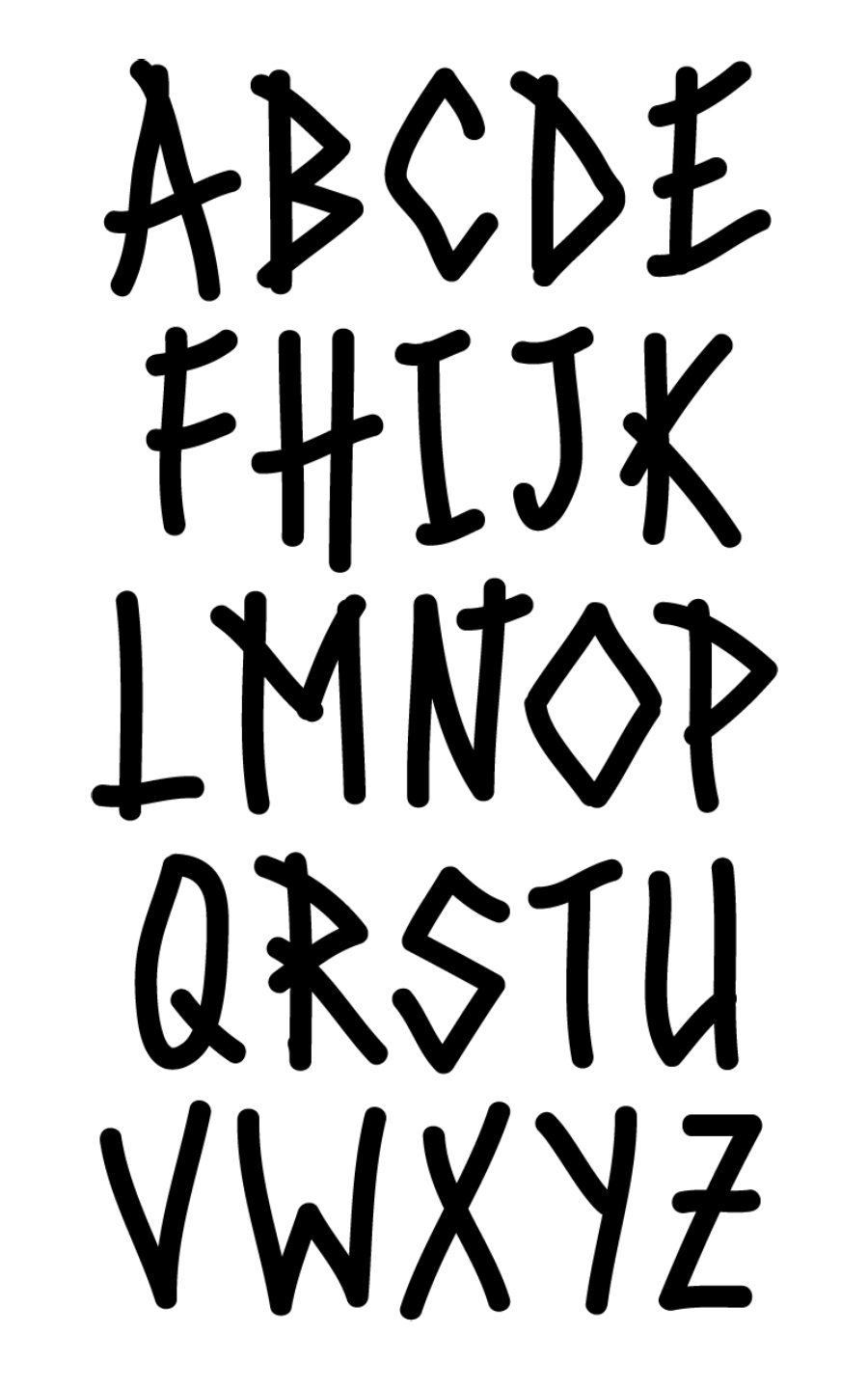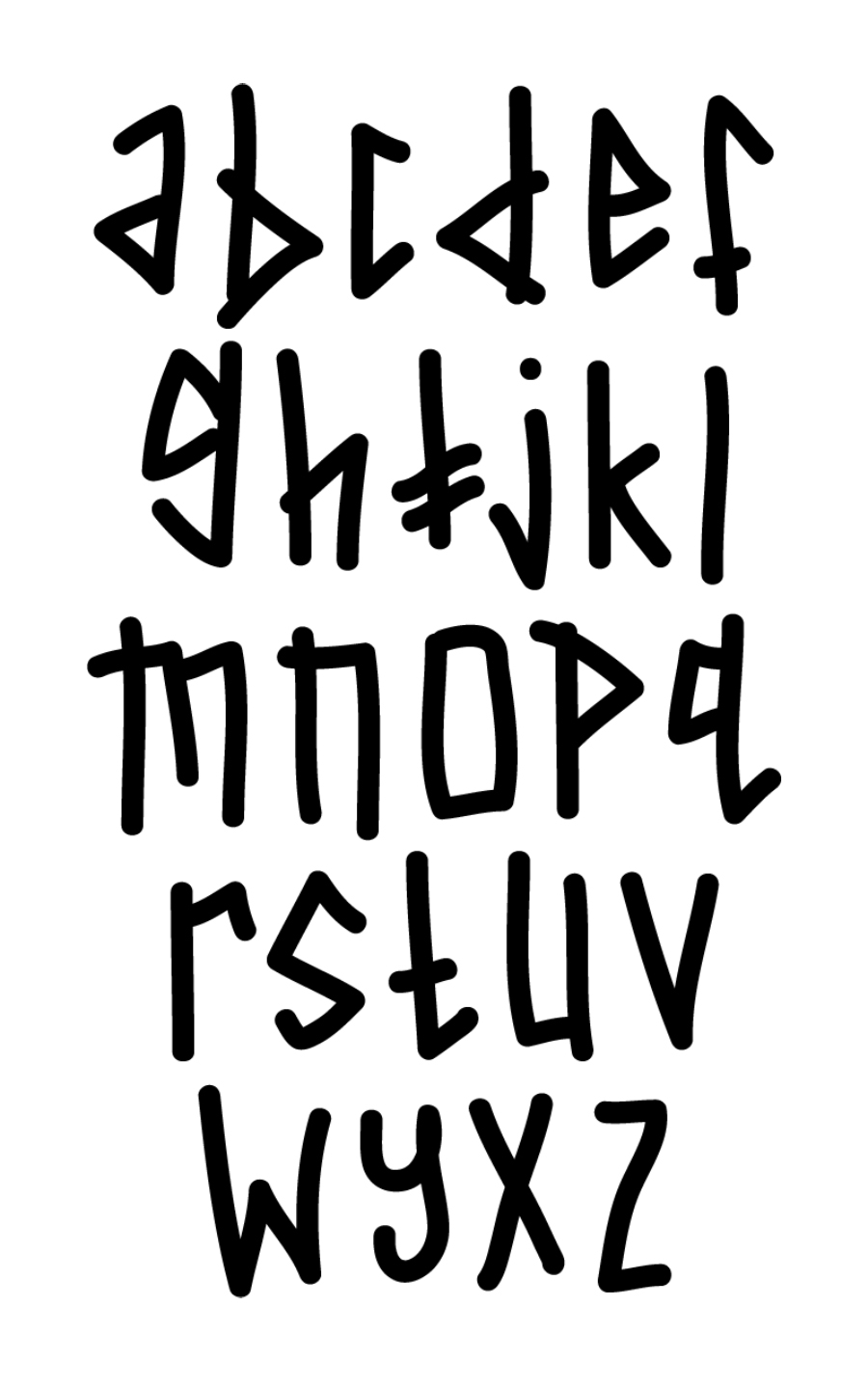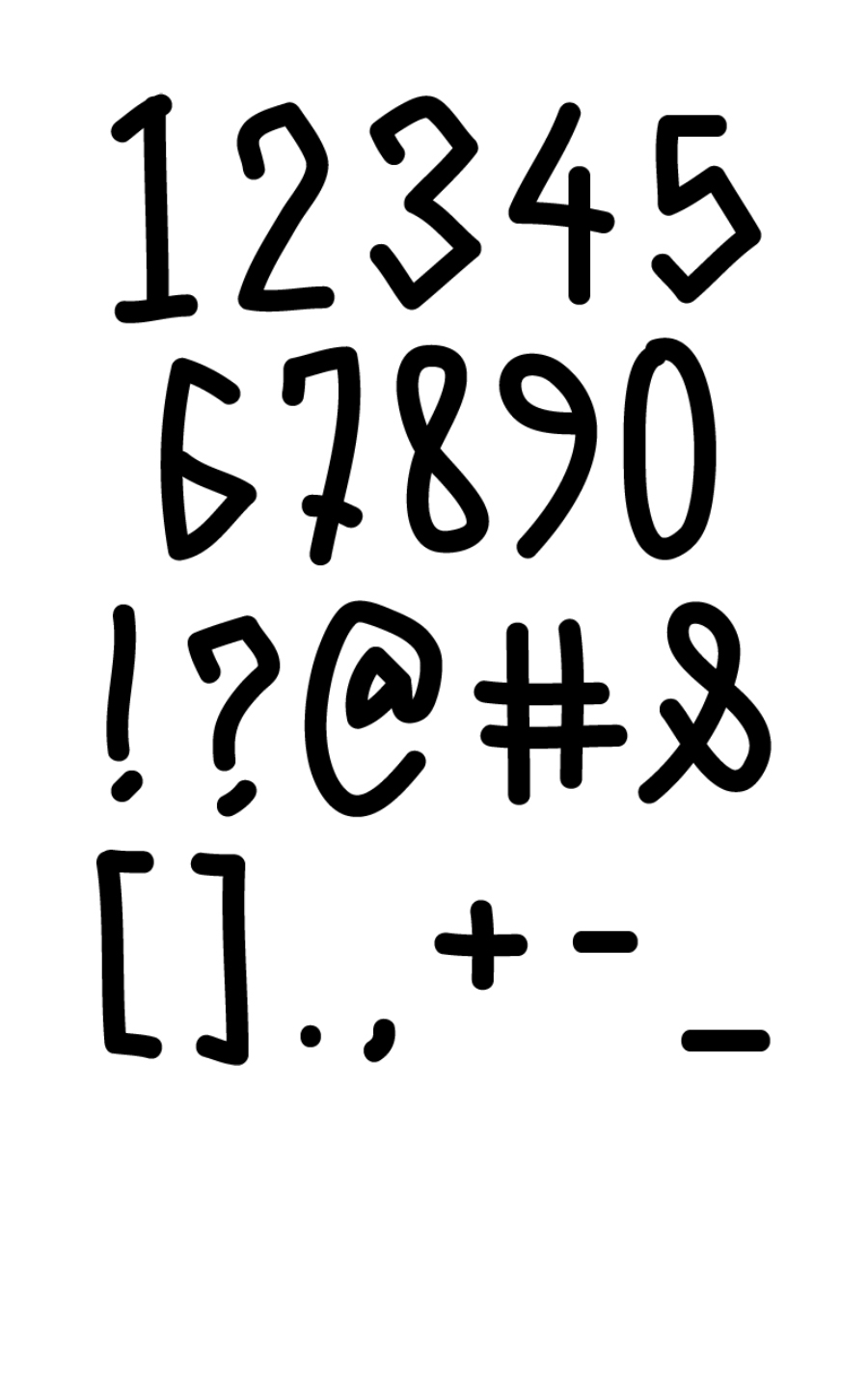
威基基日落免费字体
Waikiki Sunset Free Font
威基基日落免费字体是古希腊的主题字体,但手写,看起来很简单。这个字体对于让嬉皮士看海报广告或任何涉及年轻人的东西都很有用。这种字体只会吸引那些进入达达主义,现代主义和后现代主义的人。这个字体制作过程中没有直线工具。因此,所有的字母都是使用Adobe Illustrator中的blob画笔工具手绘的。威基基日落这个名字来自作者对海滩,日落和夏威夷的爱。威基基是火奴鲁鲁的一个海滨社区。这也是夏威夷最受欢迎的冲浪海滩,因此这个名字的想法来自哪里。